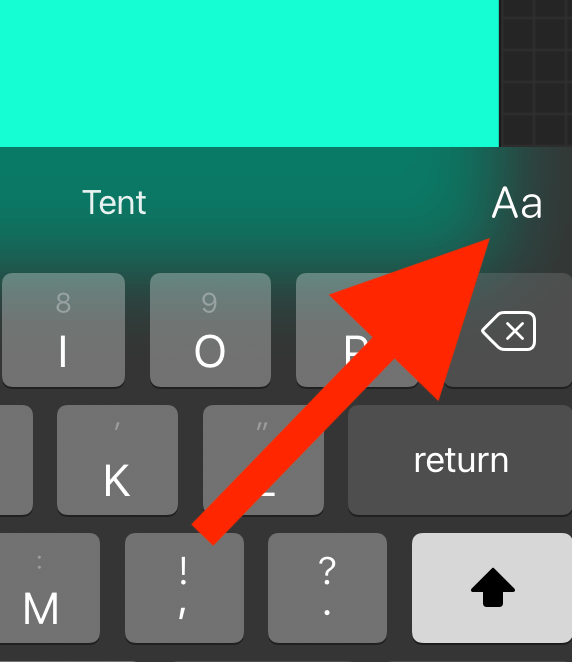
Jedną z moich ulubionych funkcji aplikacji Procreate jest praca z czcionkami i literami. Dzięki temu mogę tworzyć własne narzędzia do projektowania graficznego i brandingu bez konieczności korzystania z innej aplikacji. Możliwość kontrolowania własnych czcionek i tekstu jest niezbędna w mojej pracy.
Darmowe czcionki do procreate
Poniżej znajduje się wybór niektórych z moich ulubionych bezpłatnych czcionek, których używałem przez lata oraz miejsca, w których można je zdobyć. Jeśli chcesz używać ich do celów komercyjnych, sprawdź licencję na czcionki.
1. Nowe bezpłatne
Najlepsze dla:Nowoczesny styl komunikaty, takie jak oznakowania lub tytuły książek.
Uwielbiam tę czcionkę stworzoną przez Ryoichi Tsunekawę, ponieważ jest przejrzysta, odważna i prosta, więc świetnie się jej używa, gdy nie chcesz odwracać uwagi od wiadomości lub obrazu. Ze względu na stałą grubość drukuje również świetnie.
2. Fredoka Pierwsza
Najlepsze dla:Ilustracja książki dla dzieci.
Uważam, że czcionka Mileny Brandao jest bardzo zabawna i przyjazna dzieciom, a także oferuje kombinację wielkich i małych liter, dzięki czemu nadaje się do długich narracji, np. bajek dla dzieci.
3. Amatic SC
Najlepsze dla:Projekty w stylu indie takie jak zaproszenia ślubne.
Ta czcionka nadaje mi hipsterski klimat i wyobrażam sobie ją jako nagłówek zaproszenia ślubnego otoczonego wzorami makramy i rattanu. Został on stworzony przez Vernona Adamsa, Bena Nathana, Thomasa Jockina i Cereal.
4. Żółtkogon
Najlepsze dla:Projekty w stylu retro.
Ta stara czcionka idealnie nadawałaby się do projektów z motywami retro i przypomina mi coś, co można zobaczyć w restauracji z lat 50. lub w kinie samochodowym.
5. Rozmawiaj
Najlepsze dla:Napis w stylu klasycznym.
Użyłbym tej czcionki stworzonej przez Astigmatic do celów brandingu ekskluzywnej winiarni oferującej nowe menu degustacyjne, ponieważ nadaje ona klasyczny i czysty ton.
6. Gloria Alleluja
Najlepsze dla:Zabawny charakter pisma.
Ta zabawna czcionka stworzona przez Kimberly Geswein zostanie wykorzystana w zabawnym projekcie pisma ręcznego w stylu młodzieżowym.
7. Sacramento
Najlepsze dla:Klasyczne pismo dla dorosłych.
Kolejna czcionka firmy Astigmatic, ta wyrafinowana i płynna czcionka pisma odręcznego może być używana do wpisów w pamiętniku na zaproszeniach na wydarzenia skierowane do dorosłych.
8. Bangers
Najlepsze dla:Pasek komiksowy.
Kolejna czcionka autorstwa Vernona Adamsa, ten alfabet pisany wyłącznie wielkimi literami będzie główną atrakcją nagłówków komiksów akcji. Jest to odważna i efektowna czcionka, która szybko przyciąga wzrok.
9. Domowe jabłko
Najlepsze dla:Realistyczne pismo ręczne.
Ta czcionka stworzona przez Font Diner odwzorowuje schludny i prosty charakter pisma, jakie można znaleźć w prawdziwym życiu, tak jak można je znaleźć na etykiecie słoika domowego dżemu, który kupiłeś w niedzielę na targu.
10. Monotonne
Najlepsze dla:Plakaty filmowe.
Ta efektowna czcionka stworzona przez Vernona Adamsa od razu przyciąga twoją uwagę i świetnie nadaje się do zilustrowania klasycznego tytułu filmu.
11. Alarm szablonowy
Najlepsze dla:Futurystyczny styl.
Ta automatyczna czcionka szablonowa stworzona przez Matta McInerneya to prosta i futurystyczna czcionka pudełkowa, której można używać do wszystkiego, od graffiti po znaki drogowe.
12. Mega niespodzianka
Najlepsze dla:Pisanie bańki kreskówkowej.
Ta wielka czcionka firmy imagex odtwarza pismo bąbelkowe i oferuje małe podkreślenia każdej litery. Ta czcionka świetnie sprawdzi się w projektach kreskówek i animacji.
13. Tam, Bracie
Najlepsze dla:Styl graffiti.
Ta nowoczesna czcionka autorstwa Khurasana imituje klasyczny napis w stylu graffiti, który można zobaczyć namalowany sprayem na ulicy miasta, z tą różnicą, że jest bardziej wyrafinowany.
14. Akumaru
Najlepsze dla:Projekt gry wideo.
Ta czcionka Twinletter w futurystycznym stylu byłaby idealna do wykorzystania w nowej grze wideo lub komiksie w tajemniczym stylu.
15. Whitelisa
Najlepsze dla:Delikatne pismo w stylu boho.
Ta ledwo widoczna, delikatna czcionka pisma odręcznego pochodzi od Maulana Creative i przedstawia swobodny i czysty wspólny projekt pisma, który idealnie pasowałby do ogłoszenia o nowym dziecku lub nowego menu śniadaniowego.
16. Znak naturalny
Najlepsze dla:Kaligrafia.
Uwielbiam tę czcionkę firmy Letteralle Studios, ponieważ oferuje różne szerokości, które imitują te same zmiany ciśnienia w naturalnym piśmie kaligraficznym.
Procreate ma fabrycznie załadowaną prawie sto czcionek. Na szczęście dla nas jest tak wiele zasobów online, że niemal na pewno znajdziesz ten, którego potrzebujesz, jeśli nie jest on dostępny w aplikacji. A jeśli wszystko inne zawiedzie, możesz nawet stworzyć własny.